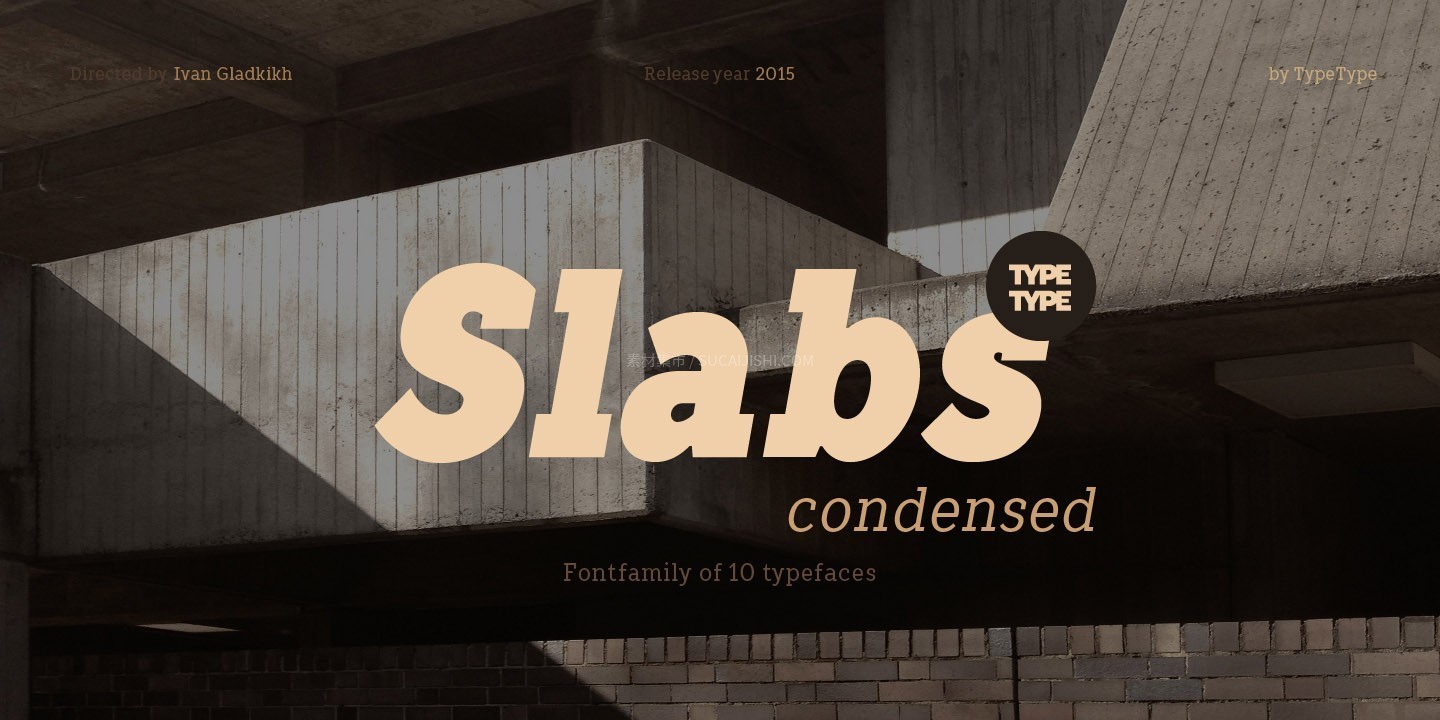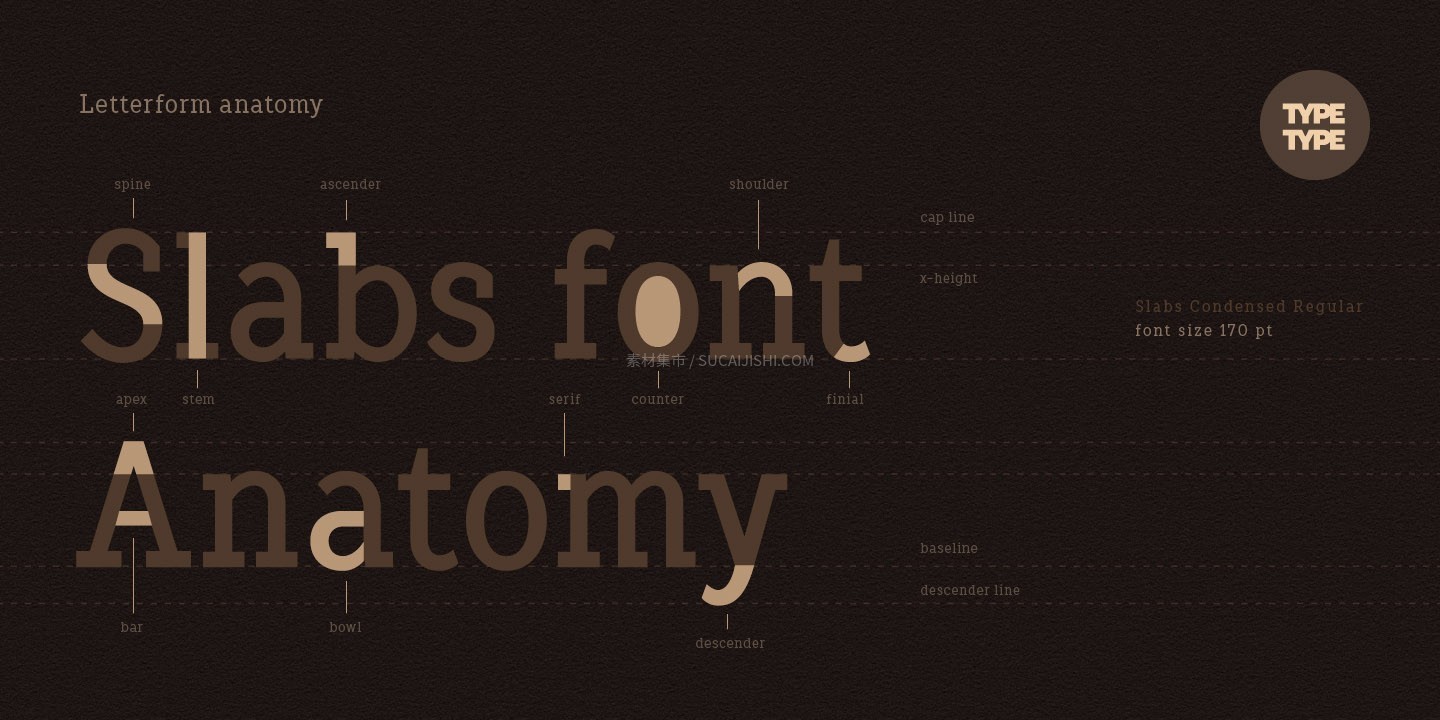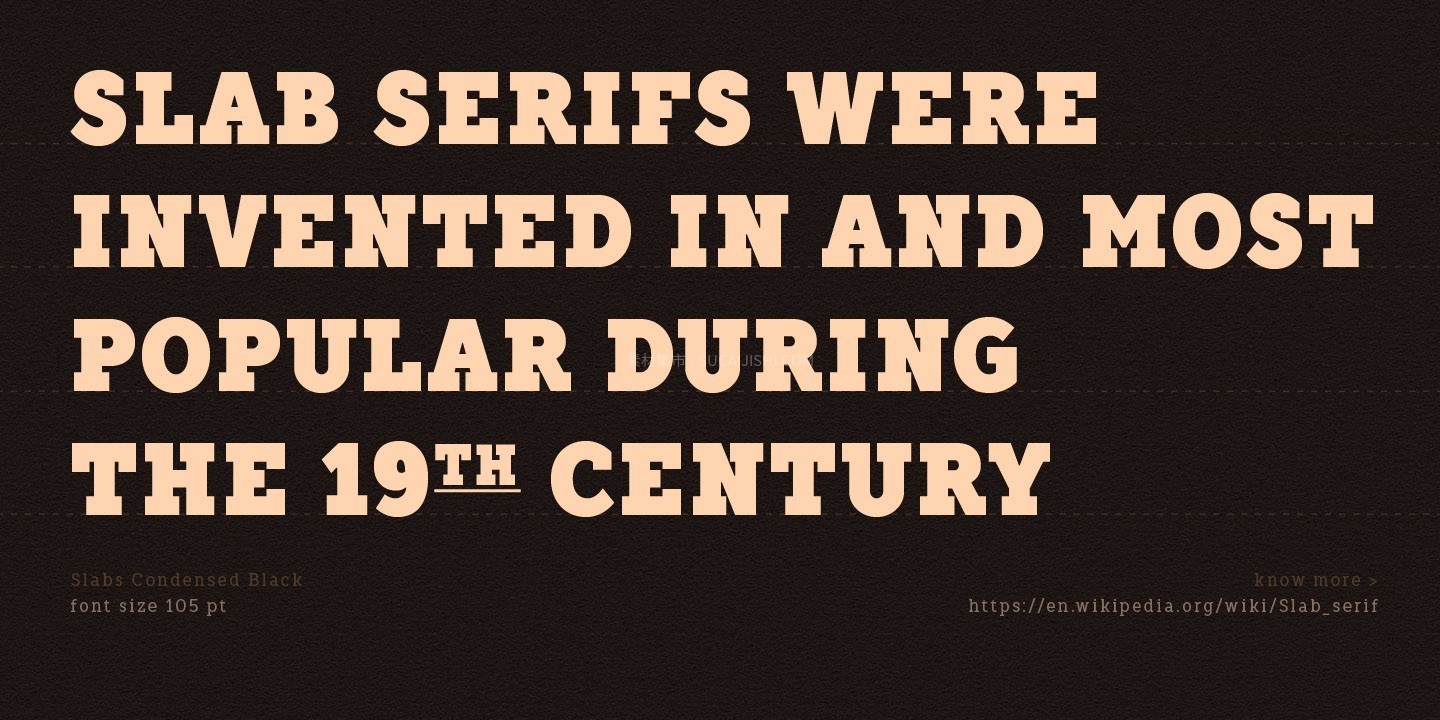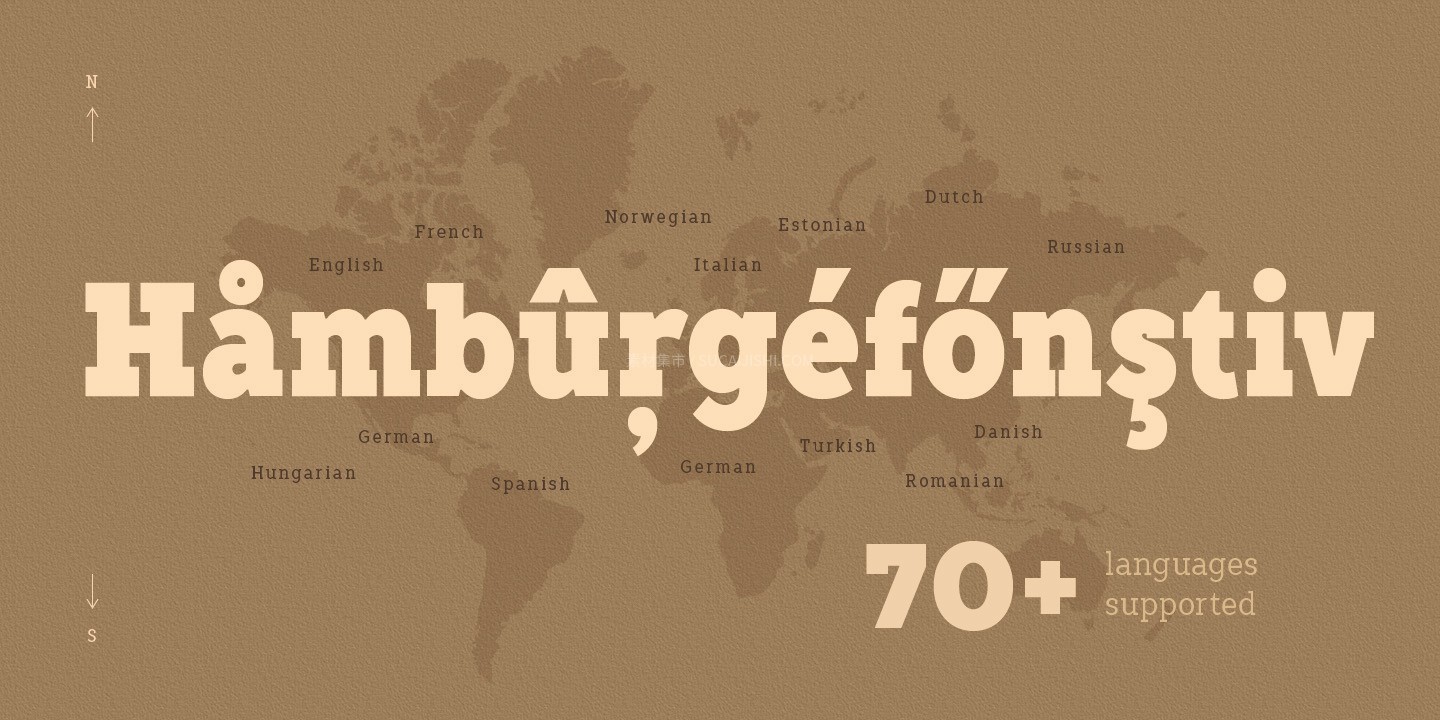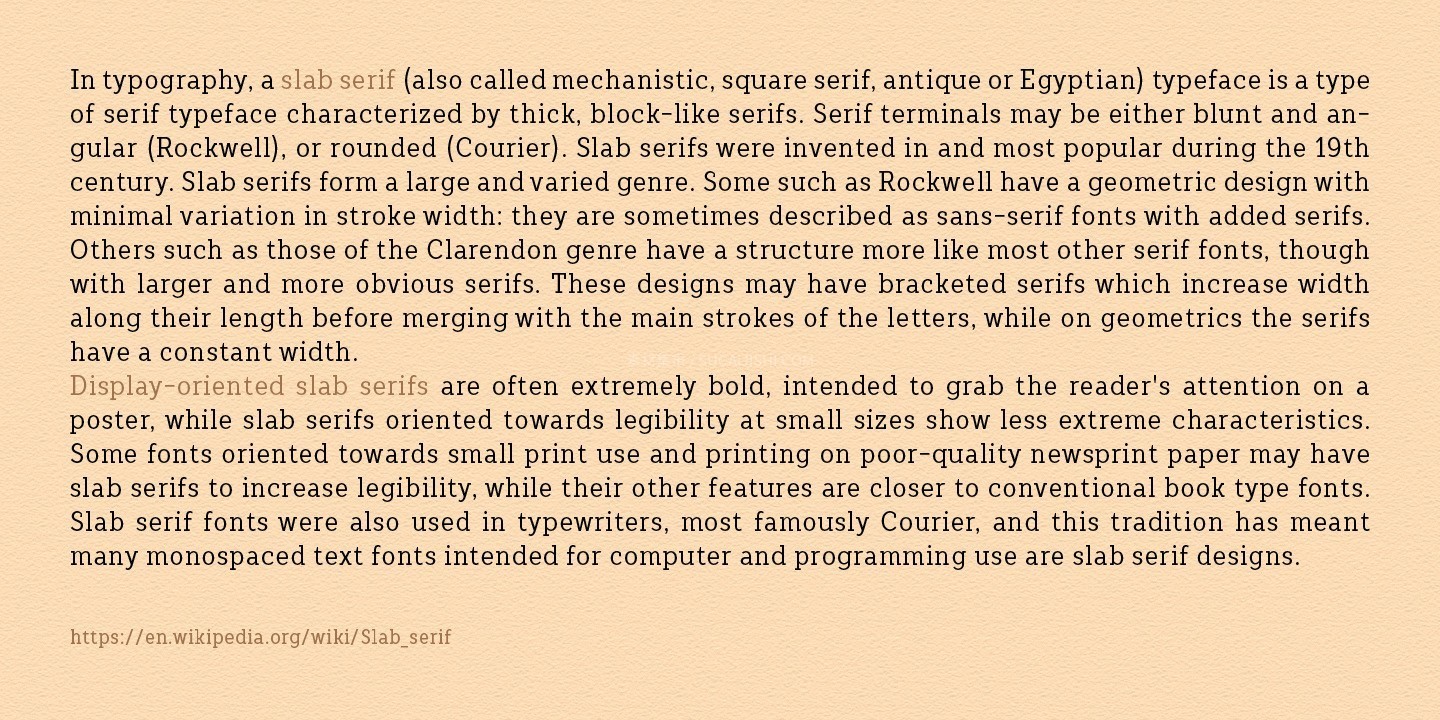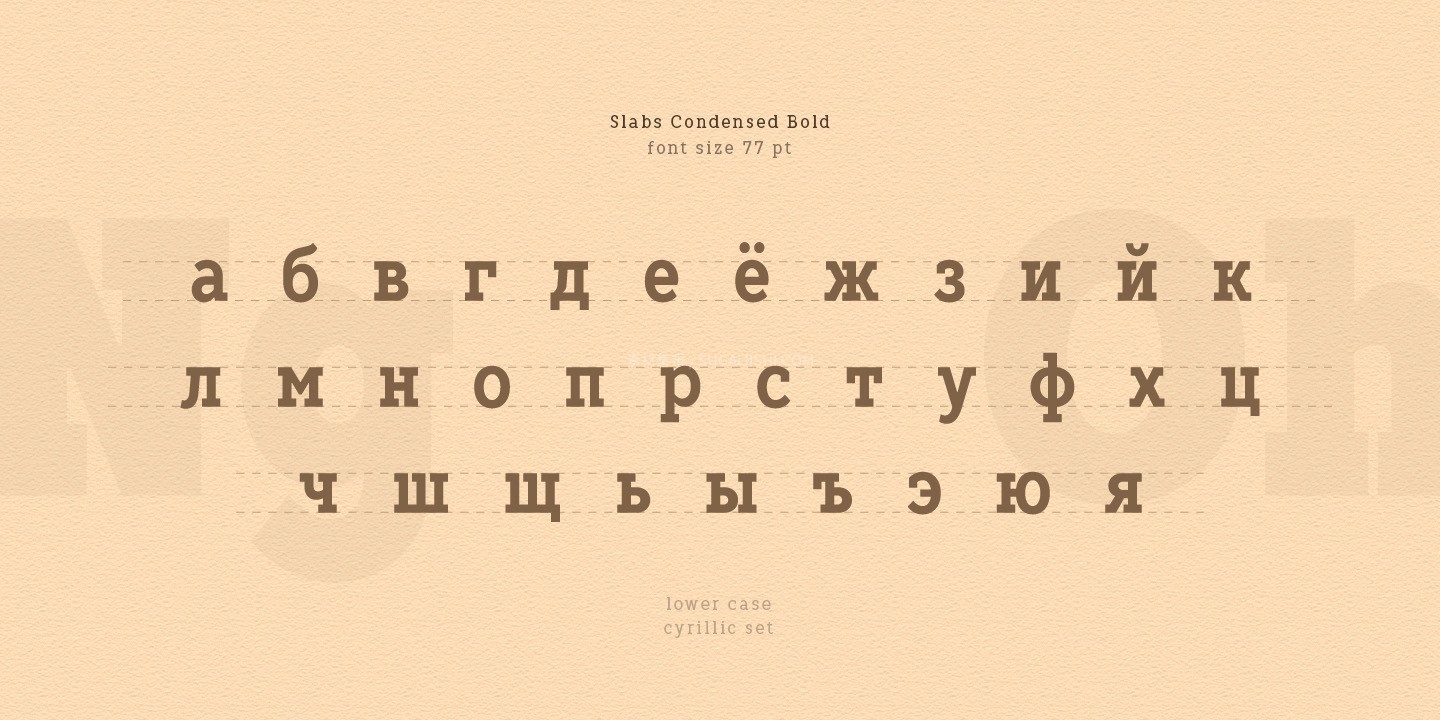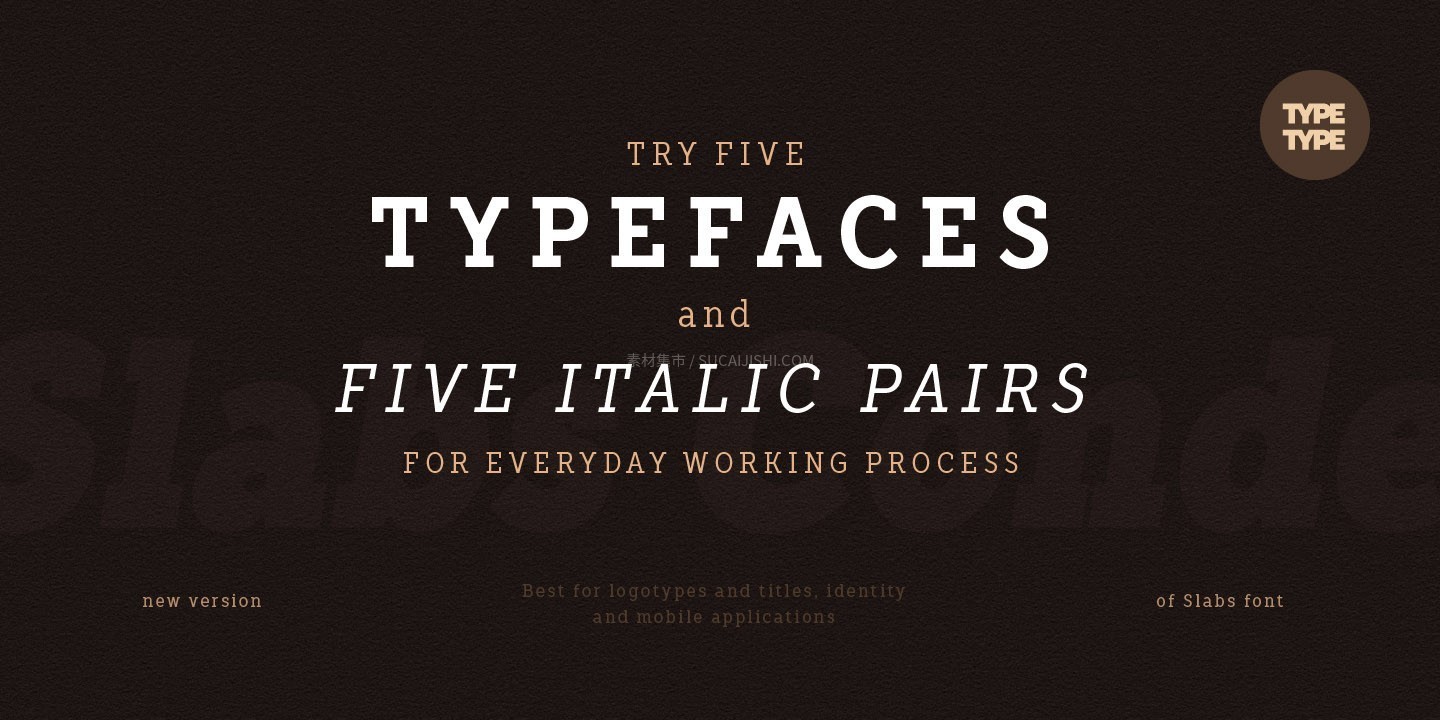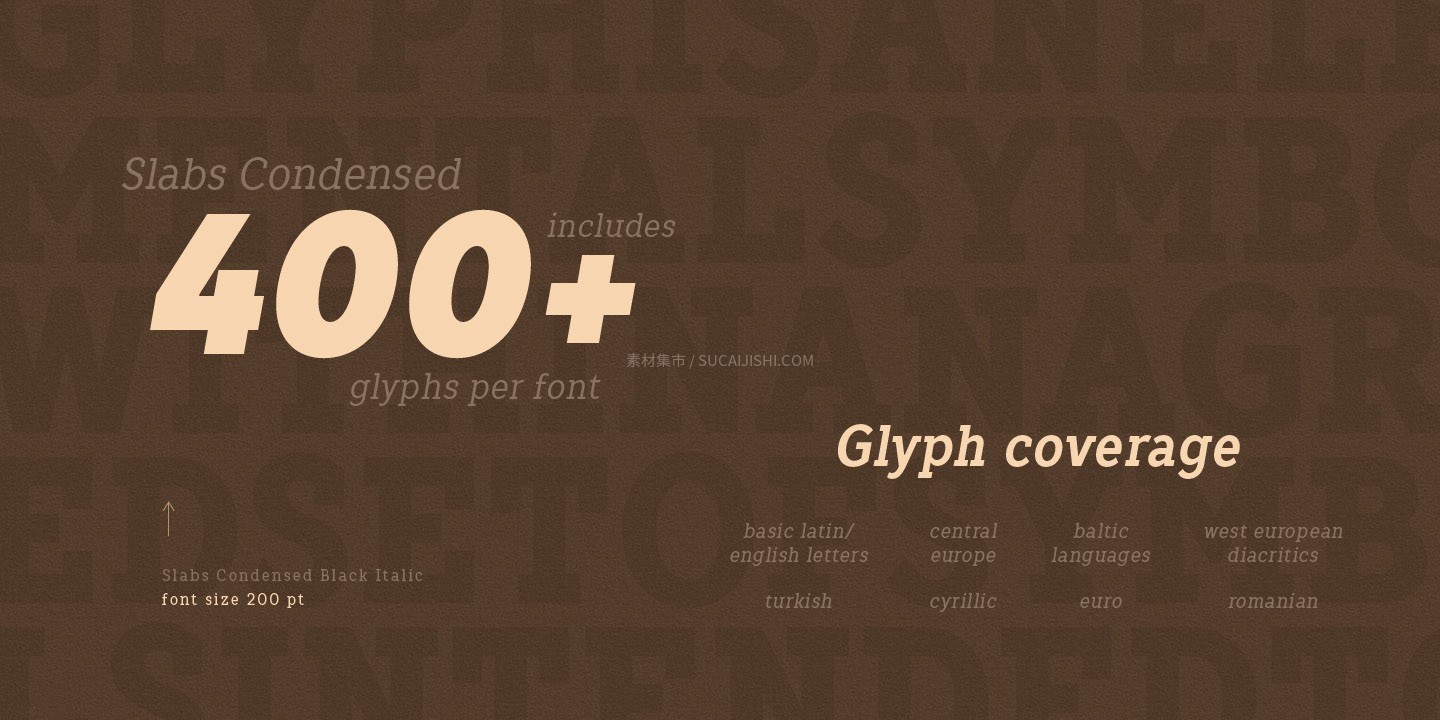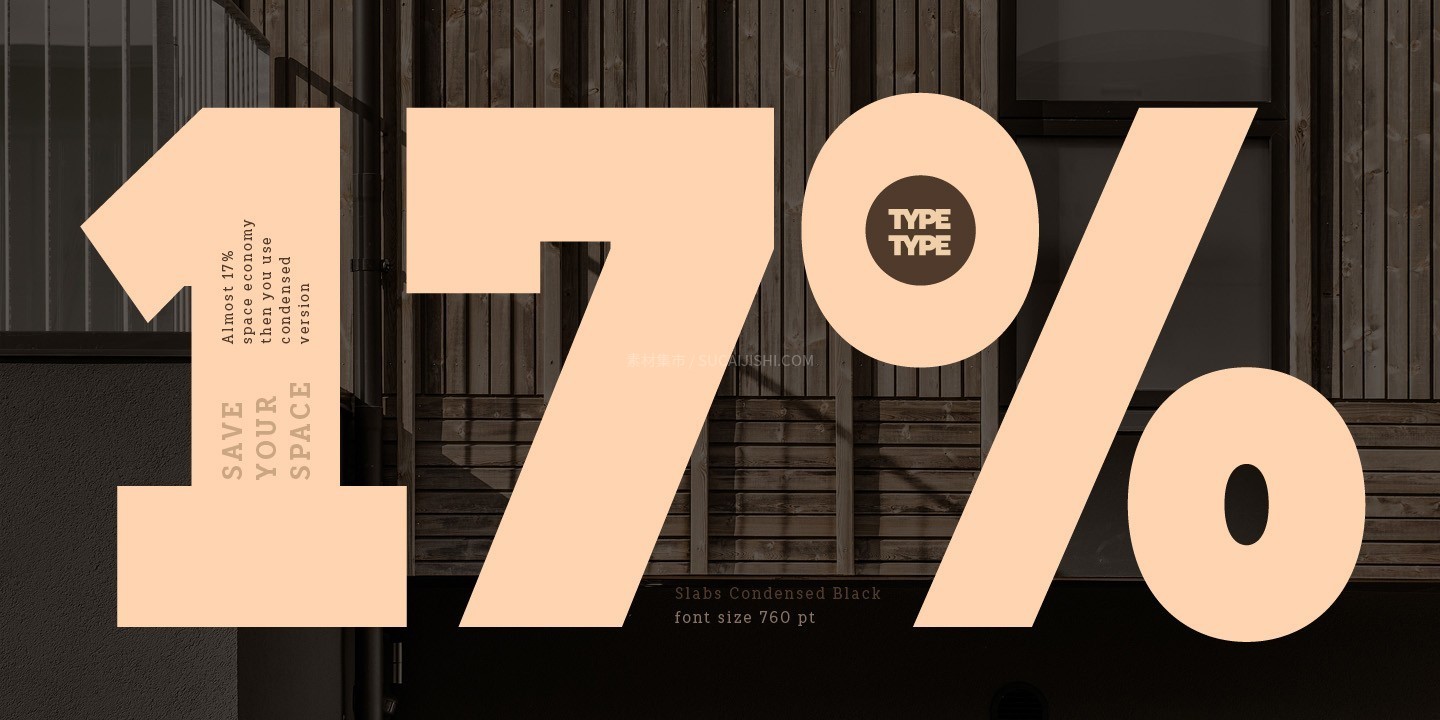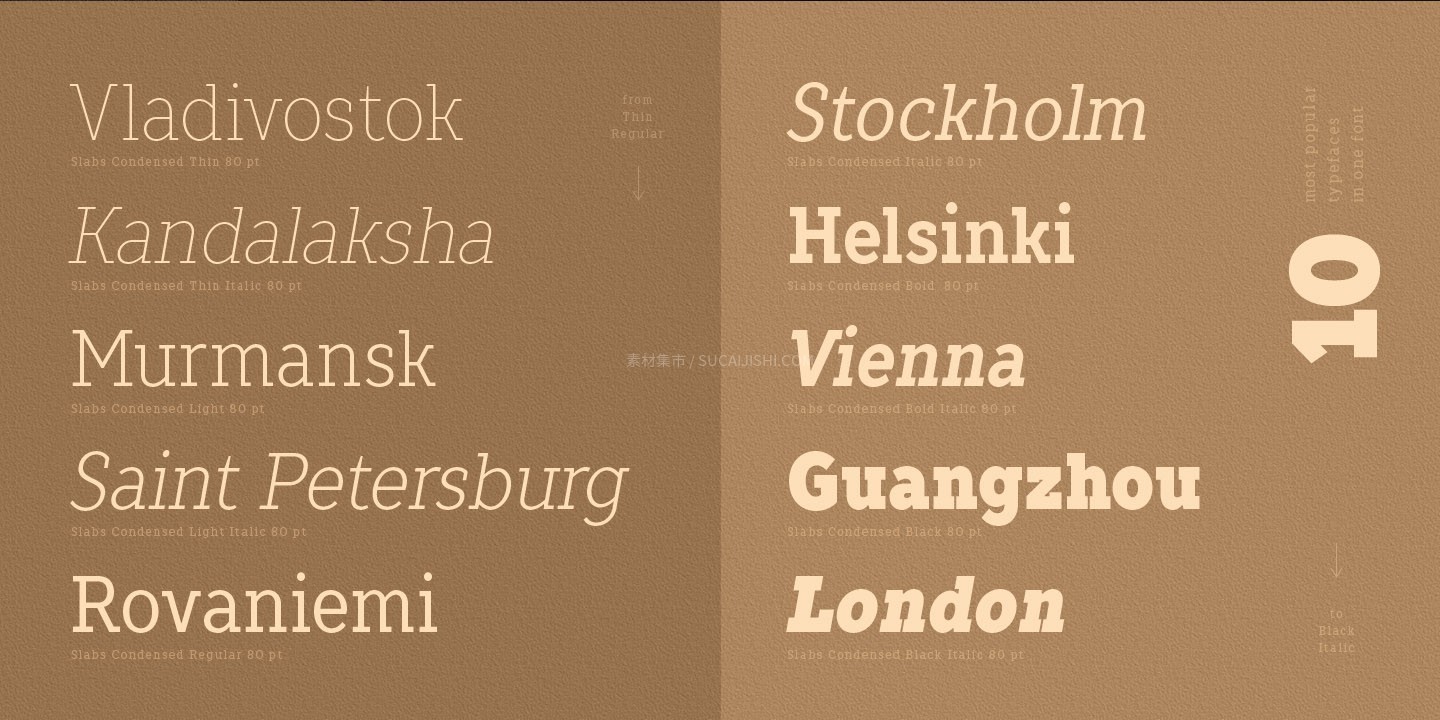
TT Slabs Condensed 多字重英文标题字体
作为 TT Slabs 字体家族的精简版,该字体专为醒目的标题和设计展示量身定制。它拥有经典的字重组合,包含纤细体 (Thin)、细体 (Light)、常规体 (Regular)、粗体 (Bold) 和特粗体 (Black),并且已针对网站、移动应用和高质量印刷材料进行了全面优化。